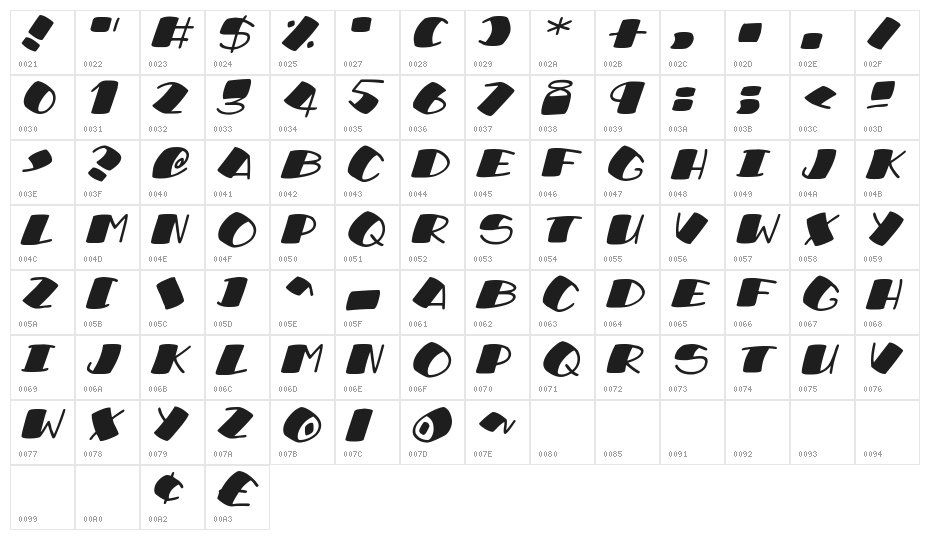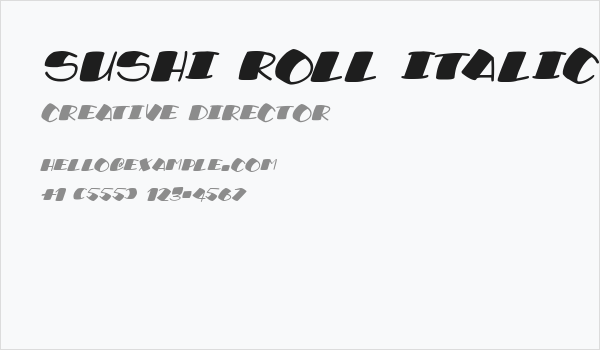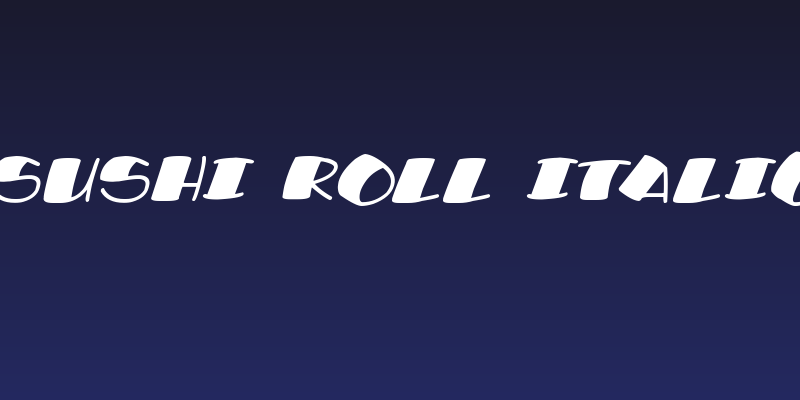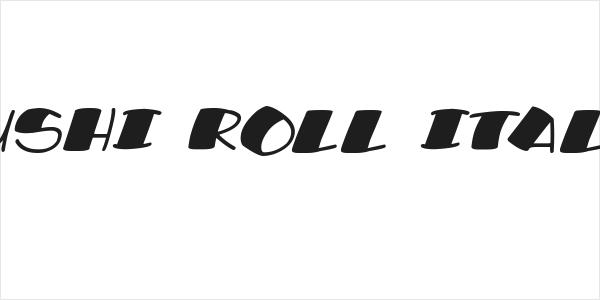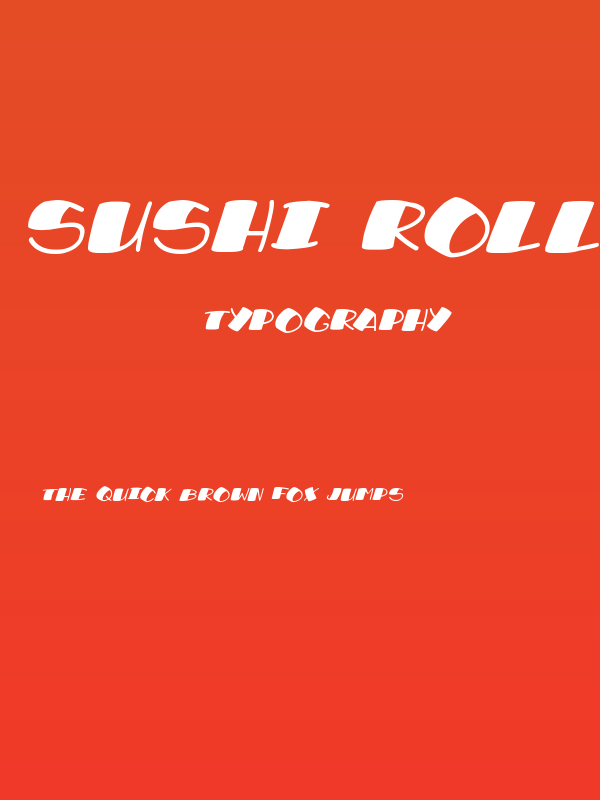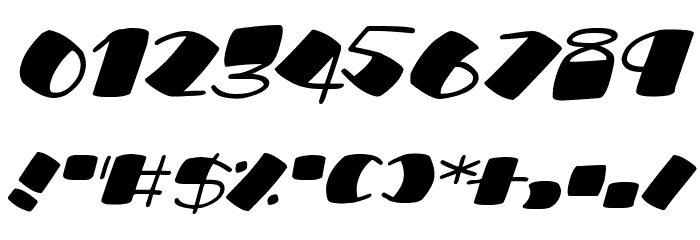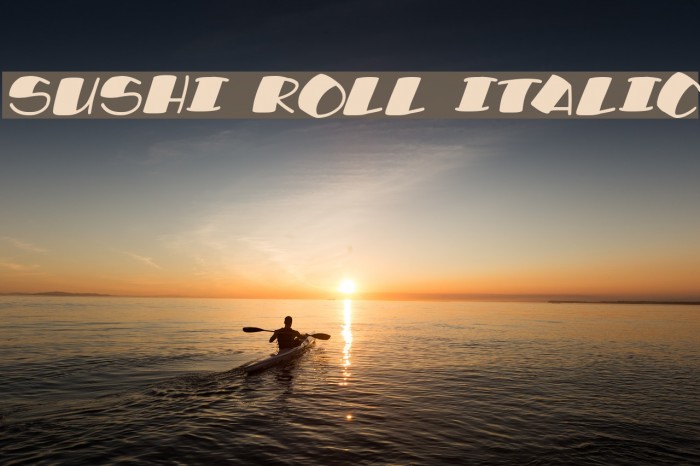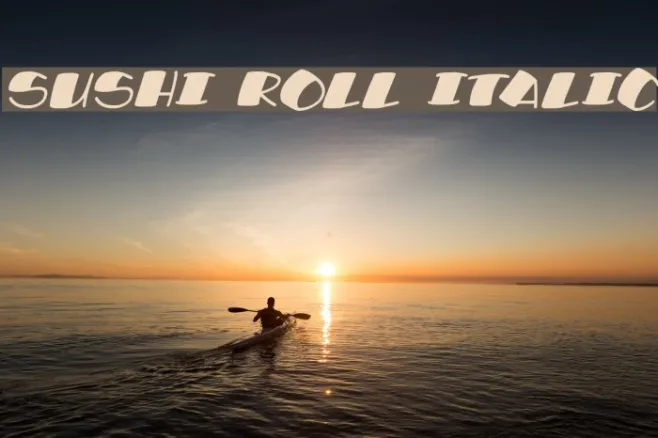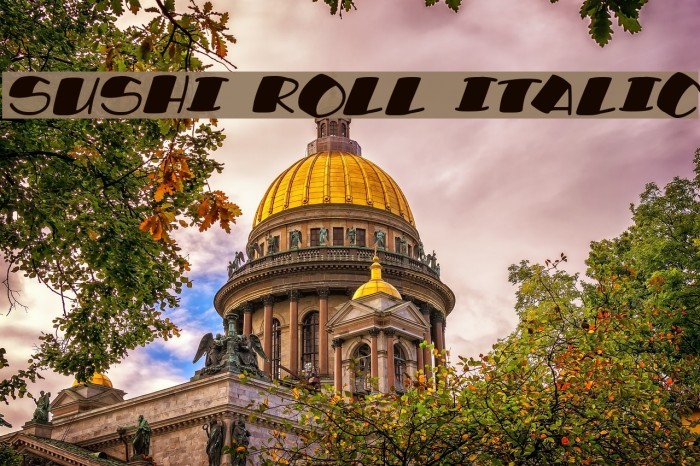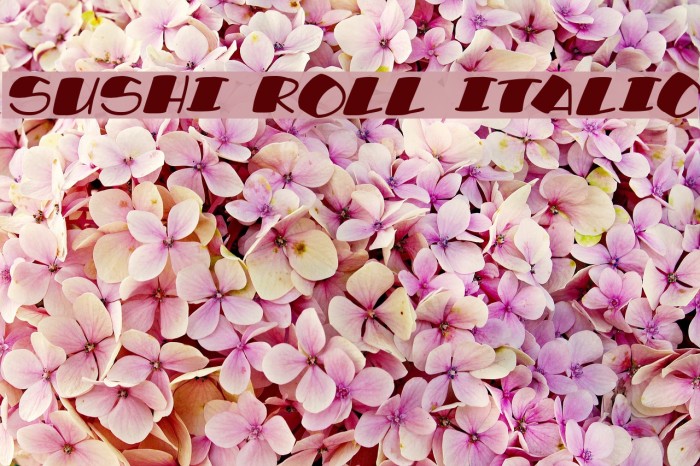
Sushi Roll Italic Font
Darrell Flood
| Estilo general | Playful, Energetic |
| Proyectos propuestos | Ideal for branding, posters, and playful graphic design projects. |